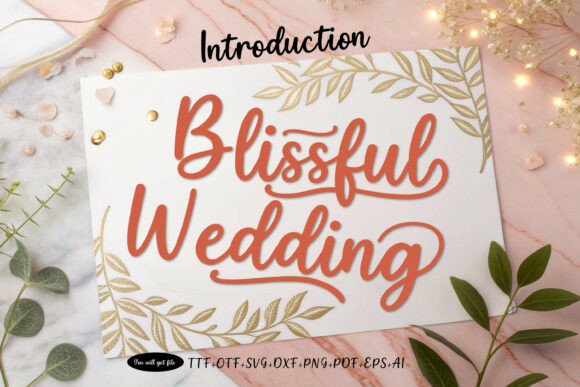
Blissful Wedding
Doğru tasarım öğelerini bulmak zor olabilir, ancak Blissful Wedding, çalışmanızı anında bir üst seviyeye taşıyan olağanüstü bir koleksiyon sunar.
İster İsteğe Bağlı Baskı (POD) ürünleri, ister düğün davetiyeleri veya sosyal medya grafikleri oluşturuyor olun, Blissful Wedding ideal bir uyumdur.